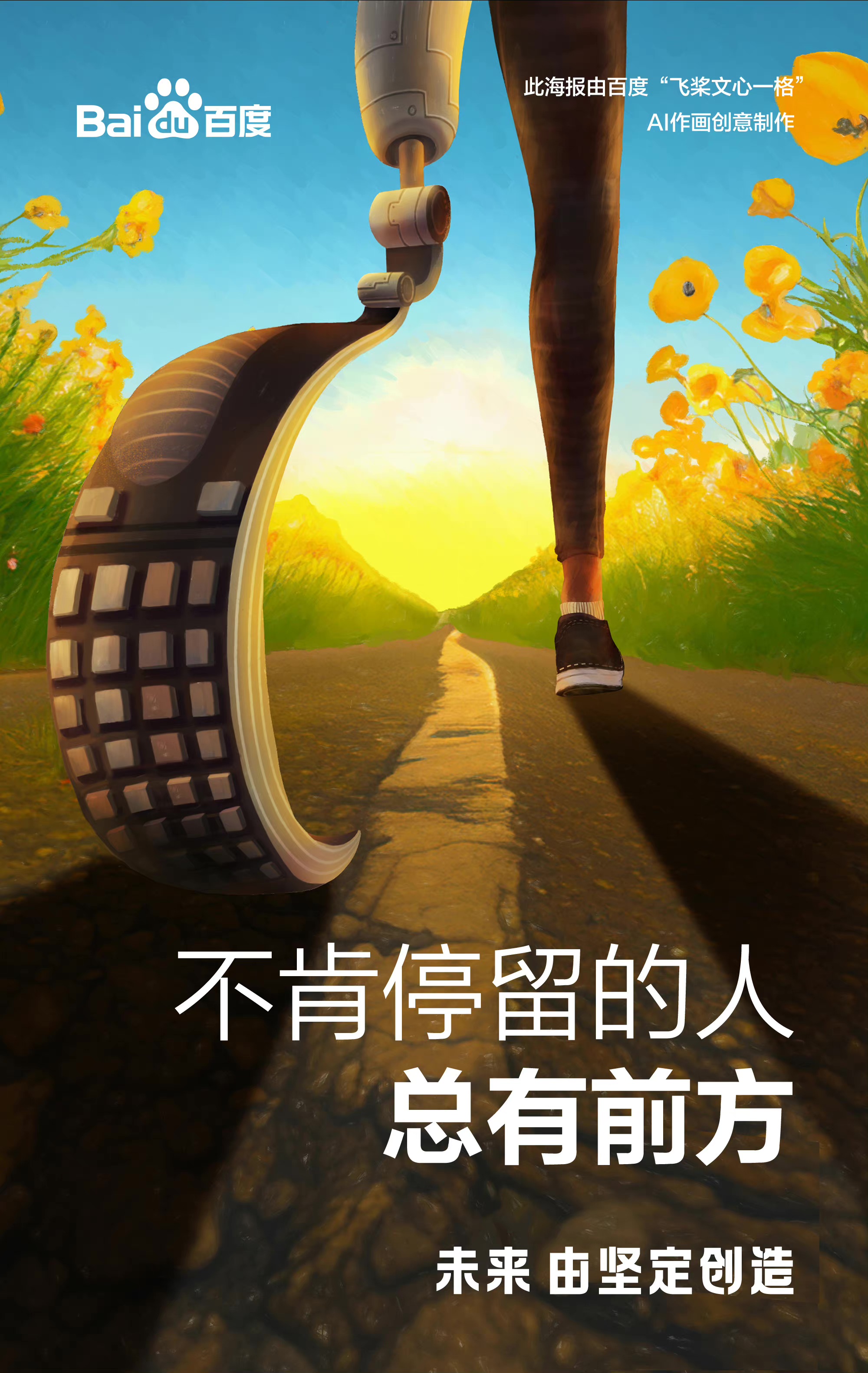
方正FW筑紫老式黑体
Fontworks,方正字库
黑体
这是一款全新设计的黑体,却能给人在金属活字时代存在过的一种似曾相识感。保持了筑紫字体系列「文字内涵信息丰富」的优点。在所有筑紫字体中这款字的信息量最大,文字本身就能洪亮地发声。横竖笔画都加上了有机的抑扬顿挫,而进一步收紧的中宫让其成为最富有情趣的黑体。单用汉字排成词句,与其他字体的区别便一目了然。